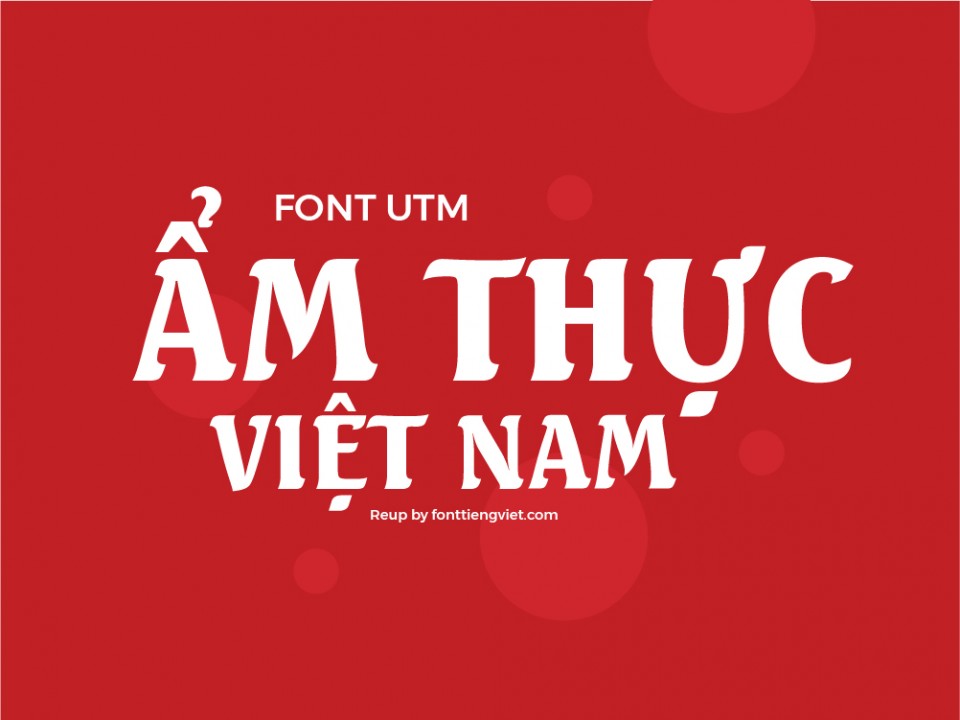
Font việt hóa UTM SeagullBold
Tải Font việt hóa UTM SeagullBold – Phông chữ tiêu đề ấn tượng miễn phí
Giới thiệu về Font việt hóa UTM SeagullBold
Trong thiết kế đồ họa, việc lựa chọn một Font Miễn Phí chất lượng luôn là ưu tiên hàng đầu của các bạn học sinh và thầy cô giáo. Font việt hóa UTM SeagullBold là một trong những phông chữ thuộc bộ UTM nổi tiếng, được tinh chỉnh kỹ lưỡng để phù hợp với bảng mã Unicode. Đây là một font chữ có nét dày, chắc chắn nhưng vẫn giữ được sự thanh thoát, giúp các sản phẩm thiết kế trở nên nổi bật và chuyên nghiệp hơn bao giờ hết.
Đặc điểm nổi bật của UTM SeagullBold
Đặc trưng lớn nhất của Font việt hóa UTM SeagullBold chính là cấu trúc hình khối rõ ràng và các đường cong mềm mại ở các góc chữ. Điều này tạo nên sự cân bằng hoàn hảo giữa sức mạnh và tính nghệ thuật. Phông chữ này cực kỳ phù hợp cho các tiêu đề báo tường, trang trí bìa giáo án hoặc làm slide thuyết trình bài giảng. Nhờ khả năng hiển thị tiếng Việt trọn vẹn, người dùng không còn lo lắng về lỗi font khi gõ các dấu thanh phức tạp.
Ứng dụng Font việt hóa UTM SeagullBold trong học tập
Đối với môi trường giáo dục, Font việt hóa UTM SeagullBold mang lại vẻ đẹp hiện đại cho các thông báo, banner sự kiện nhà trường hoặc các biểu mẫu khen thưởng. Bạn có thể sử dụng nó để nhấn mạnh các từ khóa quan trọng trong tài liệu học tập, giúp học sinh dễ dàng ghi nhớ nội dung cốt lõi. Sự linh hoạt của phông chữ này cho phép nó kết hợp tốt với nhiều kiểu font không chân khác, tạo nên một bố cục hài hòa và dễ nhìn.